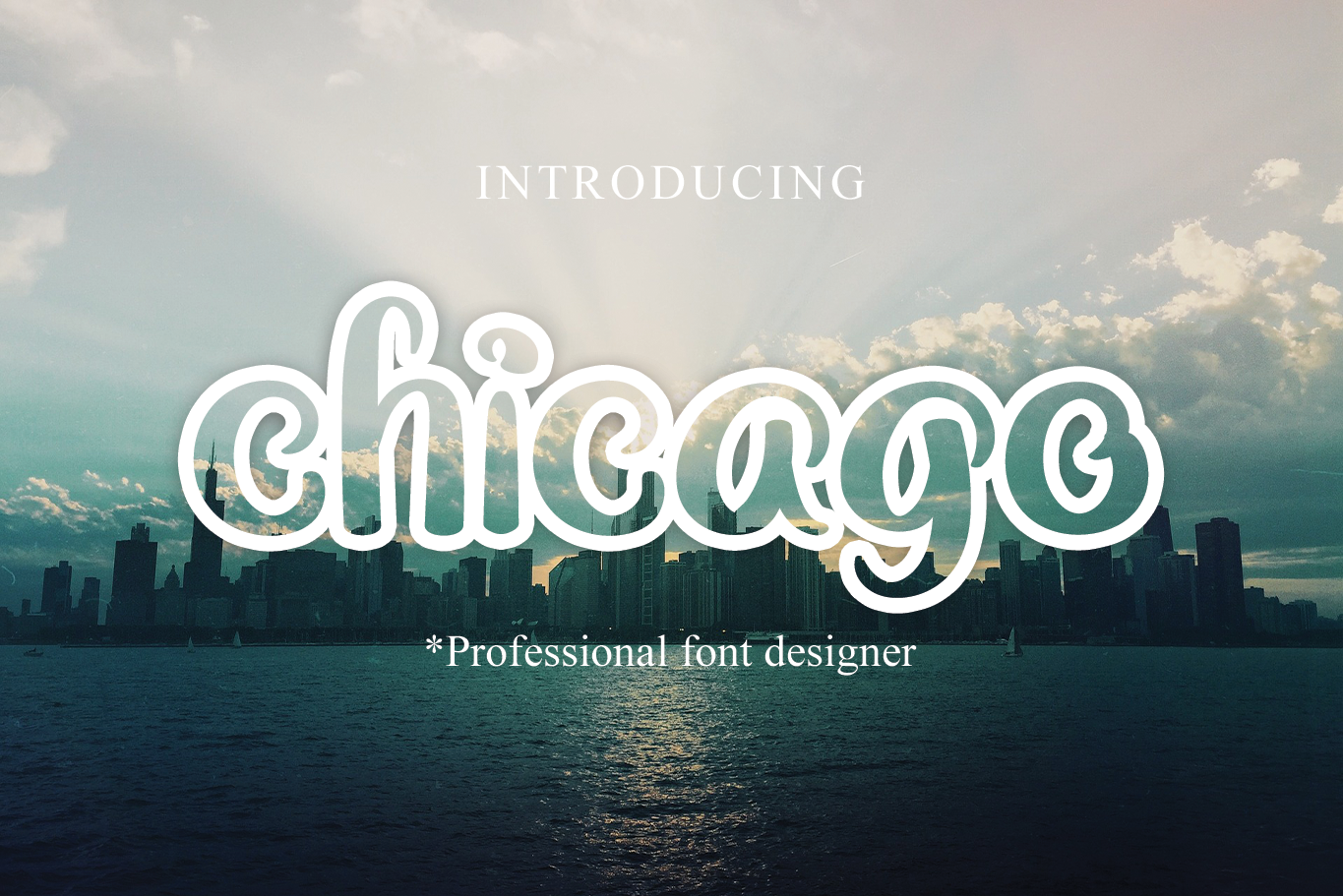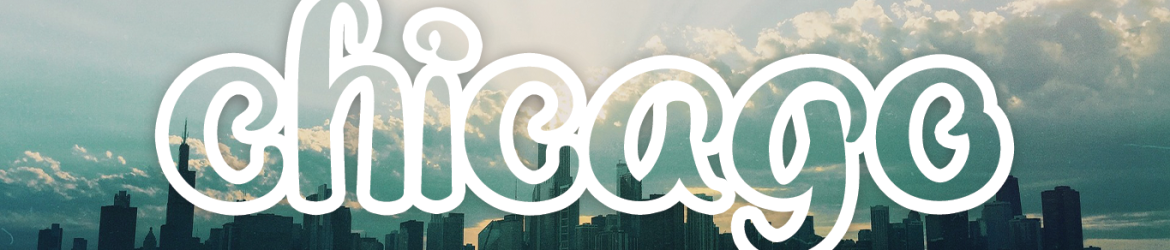
Chicago Script Font – Download Grátis
Esta é uma fonte cursive que transmite alegria e autenticidade. É perfeita para estilos de design que desejam adicionar um toque amigável e descontraído, seja ele para cartões personalizados, anúncios ou até mesmo capas de livros. A Chicago Script Font traz com ela uma sensação leve e versátil, adequada a várias aplicações, especialmente quando o objetivo é criar um design que transmita empatia e amizade. Erik Studio, o designer desta fonte, tem demonstrado seu talento ao criar designs únicos e encantadores. Com sua Chicago Script Font, ele nos apresenta uma opção de letra círculo única que combina com várias estilos gráficos, desde as criações mais tradicionais até aquelas projetadas para ambientes mais modernos. Essa fonte pode ser usada em qualquer projeto que deseje dar um toque especial e personalizado, sem deixar de lado o seu charme e elegância.